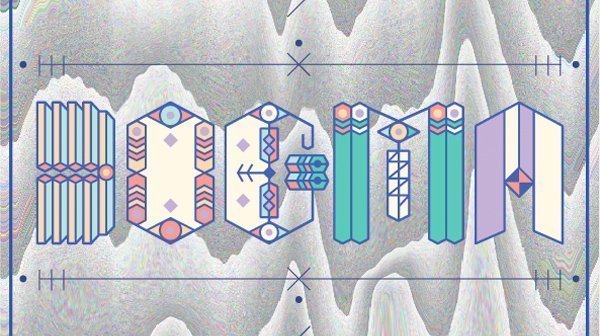
Tipografías desde Tailandia para abrir mentes
Un explorador haría lo mismo. La actitud es igual. La diferencia es que el aventurero tendría ante sí paisajes insólitos y Tanawat Sakdawisarak tiene ante sus ojos la pantalla de un ordenador. El diseñador tailandés experimenta con tipografías. Empieza una y tira de sus trazos todo lo lejos que pueda llegar. Estas son tres de sus últimas tipografías: Dogma, Baltic y Roland.
El diseñador gráfico no busca inspiración en lo clásico. Al contrario. Dice que pretende “fomentar la apertura de mente de las personas” con sus tipografías. “Parece como si todos olvidáramos lo que sabemos y solo hiciéramos cosas que nos llevan siempre a las mismas soluciones”.
“Si olvidamos la función que tiene una tipografía y partimos de la base de lo que queremos expresar, podemos encontrar nuevas formas”, continúa el licenciado en comunicación visual. “Yo acabo de empezar a hacer tipografías y me esfuerzo por que sean fáciles de interpretar”.
La primera que hizo fue Dogma. Encontró símbolos indígenas y escogió los que se podían aplicar al diseño de letras. “Me inspiré en las armaduras de los caballeros. Me gustan los detalles de su vestimenta y los utilizo para explorar tipografías”.
Los primeros bocetos de sus tipografías proceden de dibujos hechos a mano. “Empiezo a hacer bosquejos hasta que encuentro algo que me gusta y entonces continúo en Adobe Illustration. Lo voy imprimiendo hasta que considero que están todos los detalles”, explica.
Para diseñar Baltic se inspiró en las anclas y en los tatuajes de marineros.
Las líneas de Roland tienen como inspiración, una vez más, las armaduras de los caballeros.